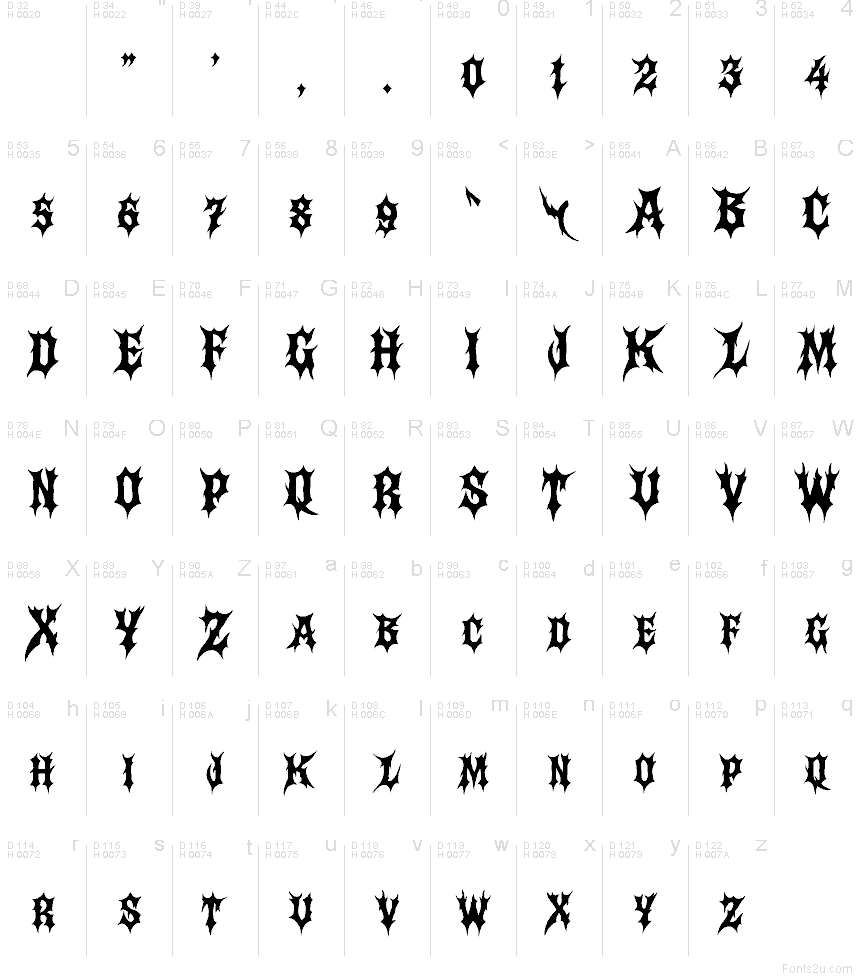
Darkness Regular
Darkness, créée par Masyafi Studio, est une police gothique gratuite au style acéré, rappelant des lettres découpées. Ses formes arborent des empattements pointus, des bords dentelés et des ruptures nettes qui confèrent aux caractères un aspect médiéval brut, tout en évitant le superflu.
Darkness est idéale pour les affiches de films d'horreur, les visuels de groupes de metal, les titres de jeux vidéo, les créations pour Halloween ou les logos inspirés du tatouage. Sa silhouette incisive impose instantanément une identité sombre et percutante. Elle est tout aussi efficace sur des packagings, des flyers d'événements ou pour des titres audacieux lorsque votre design exige une voix gothique plus marquée qu'une typographie classique.